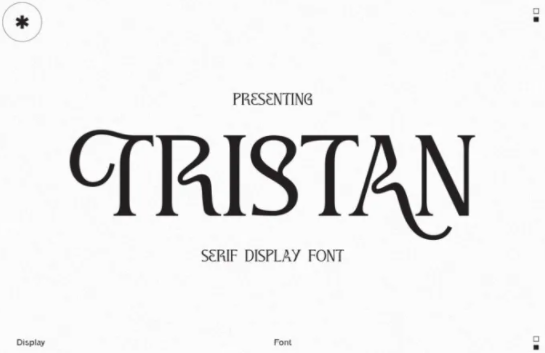
Fontbundles Tristan Font 2021
[Fontbundles] Tristan Font (2021)
Шрифт подходит для дизайна футболок, ремесел, плакатов, иллюстраций, книг, упаковки, логотипов, кружек, игр, веб, Wall Art и других дизайнерских работ.